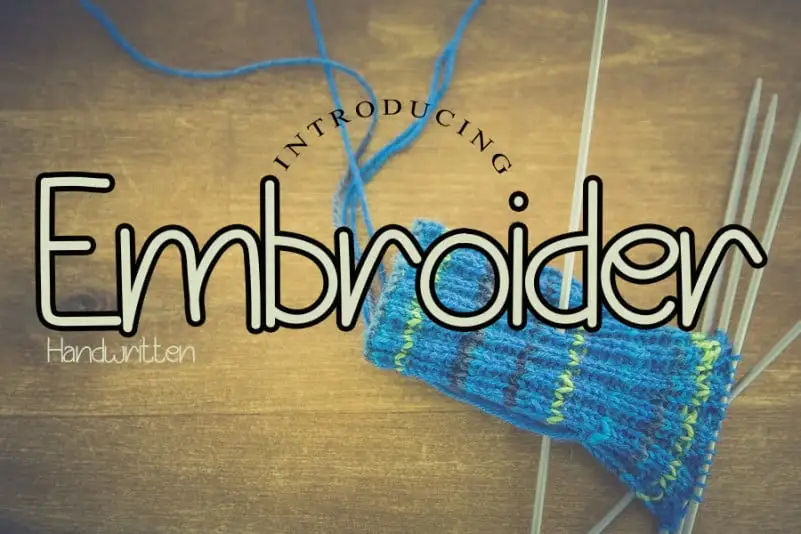
A Embroiderr Display Font é uma fonte escrita à mão que transmite suavidade e amizade, com um estilo natural e único. Seu design elegante se adapta perfeitamente a uma variedade de criações visuais. A principal qualidade desta fonte é seu estilo autêntico e peculiar; ela apenas espera que você abra sua mente para explorar como pode ser incorporada em suas próximas ideias gráficas. Não há limite quanto ao uso da Embroiderr Display Font; o espaço entre as linhas é ilimitado à imaginação criativa de quem a usa.